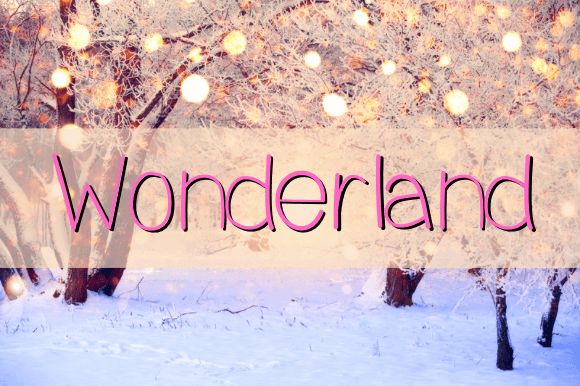
Wonderland
適切なデザイン要素を見つけるのは難しい場合がありますが、Wonderlandは作品を即座に引き立てる優れたコレクションを提供します。
POD(オンデマンド印刷)製品、結婚式の招待状、またはソーシャルメディアのグラフィックを作成している場合でも、Wonderlandは理想的です。